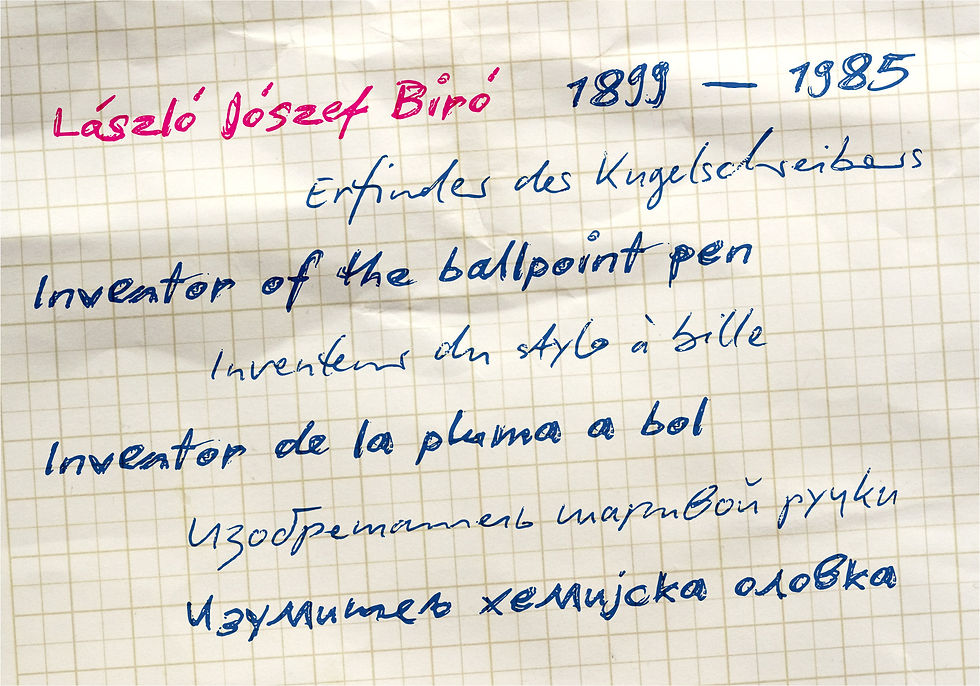
Eigentlich ist die Kalligrafie ja die Kunst der schönen Schrift…
…und eigentlich sind geschriebene Schriften als Satzschrift für den Computer ein 100%iger Unsinn.
Die »Biró Script« ist mit dem Kugelschreiber frei geschrieben.
Anders als in den üblichen Computer-Schreibschriften enthält die »Biró Script« ausser dem üblichen Alphabet mehr als 300 echte Buchstabenverbindungen (Ligaturen).
Und – die OpenType-Technik macht’s möglich: die Ligaturen erscheinen bei der Texteingabe wie von Zauberhand automatisch.
Wenn Sie also zum Beispiel das Wort alphabet eingeben, dann ersetzt das Programm die Buchstabenfolgen a l, h a und e t durch die entsprechende Buchstabenverbindung al, ha und et. Auf diese Weise wiederholen sich die einzelnen Zeichen nur sehr selten, da sie ja meistens durch eine Ligatur ersetzt werden.
Ein in der »Biró Script« gesetzter Text sieht dann einem wirklich mit Kugelschreiber handgeschriebenen Text nahezu täuschend ähnlich.
Übrigens: Die überzeugendste Wirkung erzielt man bei einer Schriftgrösse von etwa 18 bis 22 Punkt, dann entspricht die Strichstärke ungefähr der eines echten Kugelschreibers.